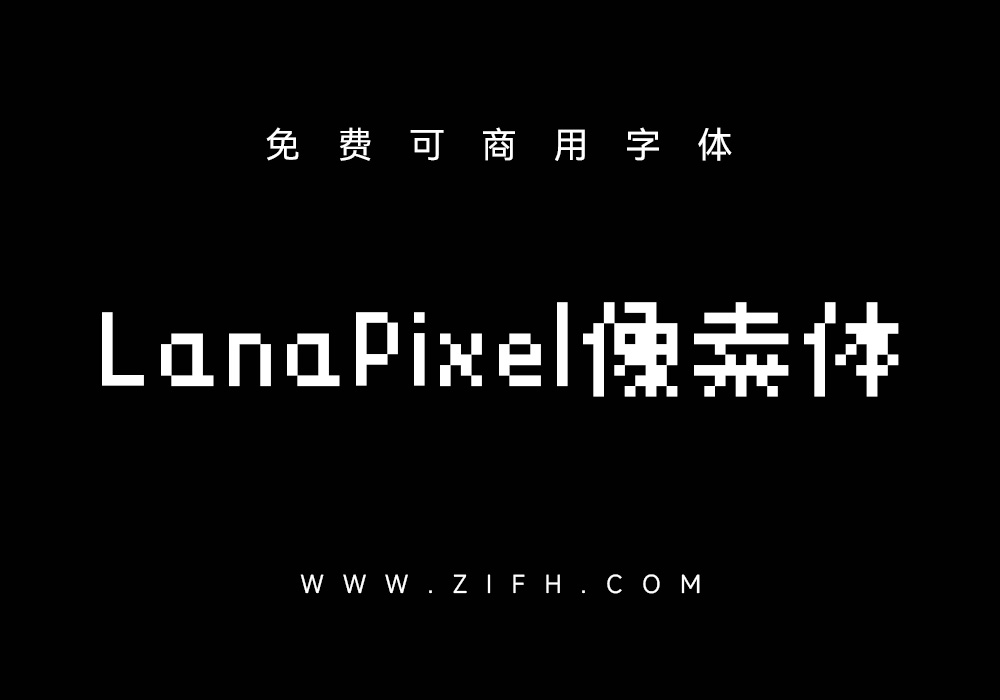
LanaPixel像素体是一款定位于像素艺术游戏的位图字体,包含大约19400个字符,支持大多数现代欧洲语言(拉丁语、希腊语、西里尔语)、土耳其语(拉丁语)和韩语(韩语),支持日语和简体中文,支持繁体中文、拉丁语、希腊语和西里尔语的字符缺少部分字符,该字体设计为以11px像素显示,由于这是一种像素字体,建议只按整数缩放(1x或11px、2x或22px、3x或33px…)以避免失真。